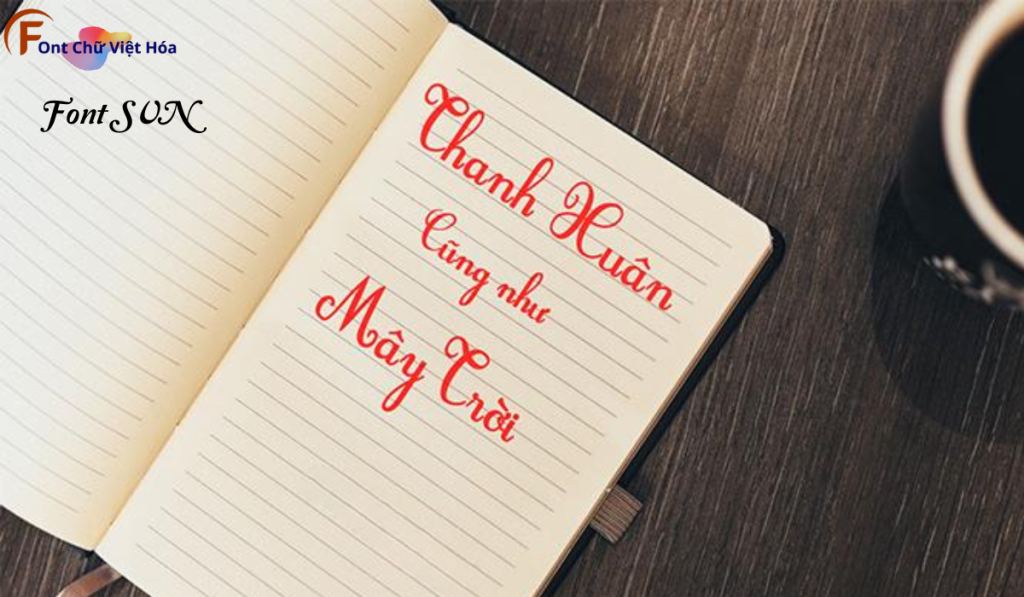
Font SVN Student Việt Hóa
Tác giả: SVN Student
Bộ Font: SVN
Kiểu chữ: Sans-serif
Font SVN Student Việt Hóa là một font chữ không chân hiện đại, thuộc bộ font SVN. Được thiết kế với mục tiêu mang lại sự tinh tế và thanh lịch, font này phù hợp cho các dự án thiết kế như website, tài liệu, và bao bì sản phẩm. Với các nét chữ rõ ràng và độ dày đều đặn, Font SVN Student Việt Hóa không chỉ dễ đọc mà còn tạo cảm giác chuyên nghiệp. Việc Việt hóa font giúp người dùng dễ dàng sử dụng trong các thiết kế tiếng Việt, mang lại sự tiện lợi và thẩm mỹ cao.